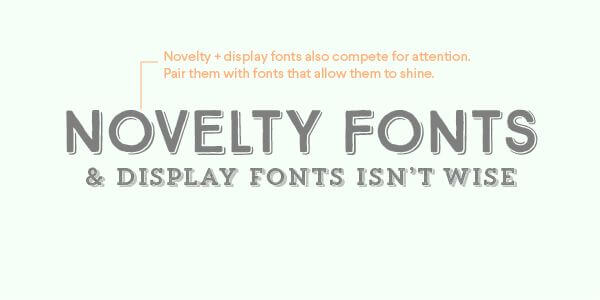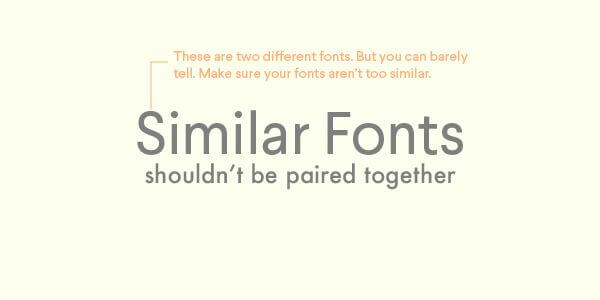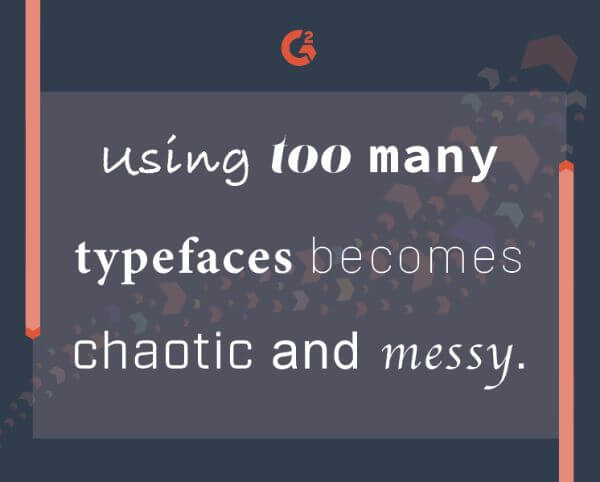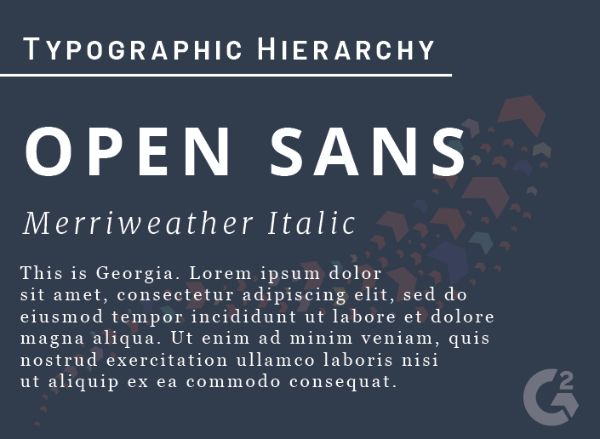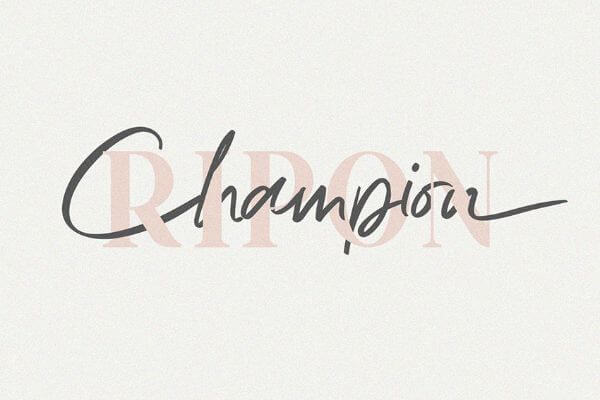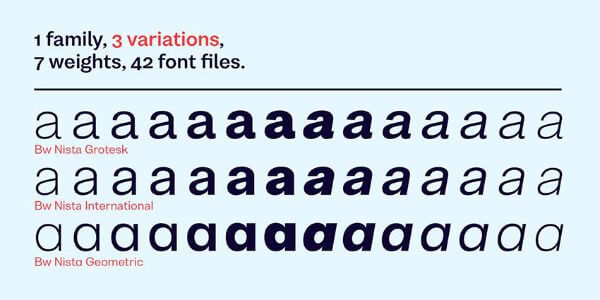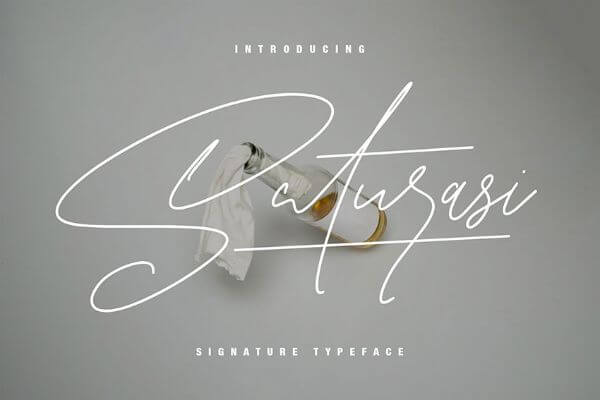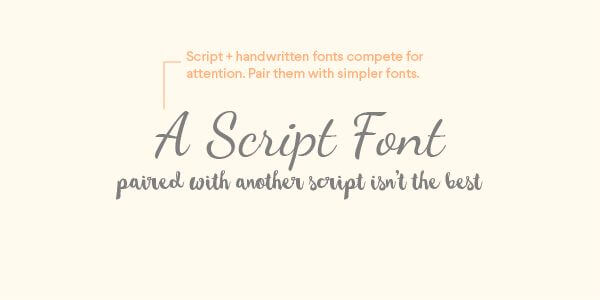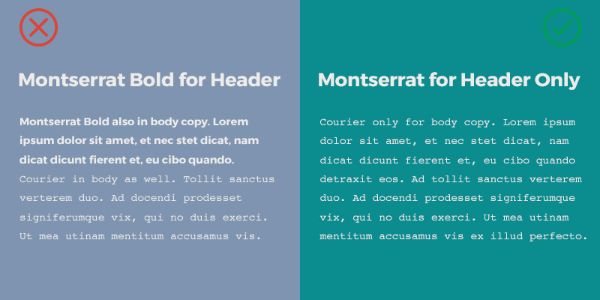
タイポグラフィーは、ブランドやサビースのブランディング、マーケティングのプロセスにおいて重要な役割を果たしてきました。ブランドのアイデンティティーを表現することができるようなグラフィックの設計がタイポグラフィーの主な役割です。
グラフィックスの大部分を構成しているのはフォントです。一種類のフォントのみで構成されたWebサイトやブログは単調で面白みのないものになってしまします。二種類、多くても三種類のフォントを組み合わせるのが確実に好評を得ることができるアイデンティティーの形成に良いでしょう。
雰囲気の全く異なるフォントを組み合わせ、デザインの価値を損ねているのをよく見かけます。以下、フォントを組み合わせる際に気をつけるべきポイントについてまとめました。
フォントの組み合わせは視覚に訴えるもので、メッセージ性があるものでなければなりません。もしそうでなければ、ページは見劣りしてしまいます。
フォント組み合わせ:
視覚に訴えるだけでなく、題材と調和することも重要です。例えば、結婚写真のWebサイトのヘッダーにグランジ系フォントを、他の部分にシンプルな手書き風フォントを使用することはできないでしょう。見た目のバランスを乱してしまうだけでなく、サイトの美学を台無しにしてしまします。
上手くフォントを組み合わせるには、様々なフォントスタイルを把握する必要があります。 テキストのパーソナリティとして分類されます。このブログでは、最も取り入れられているフォント – セリフ体、サンセリフ体、手書き風、ディスプレイ書体、ノベルティに触れていきます。
1. スクリプト体と筆記体を組み合わせない:
筆記体としても知られている、スクリプト体は現在ブームが来ています。グラフィックスにパーソナルタッチを加え、エレガントで洗練されたものにします。しかし、これらを組み合わせるのはあまりオススメできません。これを説明するのにまず、舞台上のプリマバレリーナを想像してください。
プリマバレリーナは基本的にリードダンサーと一緒に舞台で踊る事はありません。例外として、あまり彼女にとって重要ではない役所の個性的なキャラクターやバックダンサーと一緒に踊る事はあるかもしれませんが。スクリプト体と筆記体はそれのみで使用するか、全く雰囲気の異なるものと組み合わせましょう。
2. 類似したフォント同士の組み合わせは避ける:
スタイルの似たフォント同士を上手く組み合わせるのは至難の技です。どういう事かと言うと、スタイルが似ているフォント同士だと区別がつきません。また、真逆のスタイルだとまとまって見えません。このような組み合わせは避けるようにしましょう。似たようなフォント同士を組み合わせたいのであれば、同じフォントの様々なバージョンを試すと良いでしょう。たとえば、italicと太字のitalicを組み合わせる事でダイナミックなデザインにする事ができます。しかし、やりすぎは禁物です。
3. ちょっとまった!そのフォント組み合わせ(DisplayとNovelty):
重厚なフォントはページを強調するために用いりますが、そのようなフォント同士を組み合わせた場合、強調の効果がなくなります。displayとnoveltyの組み合わせは、両者の個性が喧嘩してしまいグラフィックがただ目障りなものになってしまいます。displayとnoveltyはそれのみで使うか、もしくはより線の細い軽い印象のフォントを用いることでタイポグラフィーがバランスのとれたものになるでしょう。
4. 複数種類のフォントを混ぜない
ご覧の通り一つのグラフィックやページに複数のフォントを組み合わせると、散らかってまとまりがないように見えます。何千種類の中から、適切なフォントを選ぶのは簡単なことではありません。どれを使うか悩んでも二種類、多くても三種類に時間がかかっても絞りましょう。
確かに現実の芸術作品では、複数のフォントを組み合わせている場合もあります。しかし全体の雰囲気としてどうか、複数のフォントを取り入れる前に考えましょう。
5. フォントのウェイトとサイズを工夫する:
二種類のフォントを組み合わせる際、様々な文字の太さ、サイズ、行間のスペースを試すのが良いでしょう。デザインは奇抜すぎずバランスが取れたもので、よく考え抜かれたものであるよう心がけましょう。雰囲気の似た二種類のフォントを組み合わせる代わりに、一種類のほんとでスペースや、ウェイトを工夫することでエッジの効いたデザインになるでしょう。
6. ビジュアルヒエラルキーを考慮する:
タイポグラフィーでは、ビジュアルヒエラルキーを考慮するのも必要不可欠です。フォントを使い分けるのは、特定の文字のかたまりが他を抑えて強調されるようにするためで 、それを実現するために太字を細字と組み合わせたりします。もしくは、スタイル、ウェイト、サイズ、カーニングを試してみるのも良いでしょう。
例えば見出しにNista Groteskを、ボディーコピーにAntique Regularを組み合わせるのもオススメです。ページの雰囲気などに合わせてNista Groteskの文字の太さを変えてみるのも良いでしょう。最近では見出しにセリフ体、ボディコピーにサンセリフ体を用いてることが多く、この組み合わせは新聞や商用ブログに適しています。
7. フォントデザイナーが手掛けたフォントは乱用しない:
エネルギッシュな手書き風フォントでしたら、Saturasiがオススメで、Lostfield Sansとマッチします。(上のイメージのように)Saturaiはサンセリフ体の凝縮型で、複数のウェイトを持っています。
8. フォントデュオ素材は積極的に取り入れる:
現在では多くのWebサイトのプラットフォームで、デザインに直接導入可能な厳選されたフォンデュオ素材が提供されています。デザイナーがすでに一番良いフォントの組み合わせを絞り込んでいるので、オンラインプラットフォームからすぐにダウンロードでき、モード(ウェディングカードやソーシャルメディアの投稿など)により使い分けることができます。
上記はRioponというフォントデュオ素材で、優雅さと洗練を表現しておりウェディングカードやファッション関係の資料にピッタリです、
9. フォントに役割を与える:
フォントに役割を与えることで個性を作り出すことができます。特定のフォントを見出しに、それより細いものをボディーコピーに、さらに線が細いフォントをキャプションに用いることで全体として見た際にシナージ効果が期待できます。左上のように、二種類のフォント組み合わせに割り込む形で文書やページの途中で急に新しいフォントを取り入れるのはオススメできません。見た目の調和が損なわれ、フォントを適当に組み合わせているように見えてしまいます。
10. フォントの雰囲気を重視する:
それぞれのフォントの個性や雰囲気も大切にしましょう。例えば、ImpactとMTF Cool Kid.は組み合わせるのに適していません。Impactは太く、重厚な書体なのに対し、 while MTF Cool Kidはシンプルで遊び心溢れる書体です。 個性が全くことなるこれらのフォントは調和しません。上の例も参考に紹介しましょう。
Nexa Rust SlabとAirstreamといったフォントが組み合わされていますが、個性が違うだけでなく雰囲気も全く合わないため、読み手に一体感をあたえることもできません。適切なフォント組み合わせは、個性と雰囲気が似ていることが前提です。フォントだけでなく、タイポグラフィーとしてどれだけメッセージを伝えることができるのかが重要です。
Envato Elementsにも評価された Font Pairでは優れたフォント組み合わせを提供しています。サイトを無料で閲覧、ダウンロードできます。サイト内のフォントからも選ぶことも可能です、もしくは用途に合わせてカデゴリーからも探すことができます。
フォントの組み合わせは、アートであり科学です。美的感覚だけでなく、精度も重要となってきます。正解はありませんが、視覚に訴えるものでメッセージ性があるものであれば人々の心に届かせることができます。平凡でベーシックなものより、周囲の人に聞きながら適切な組み合わせを選びましょう。十分な時間をとり、誰も見たことないような素晴らしい組み合わせを生み出しましょう。